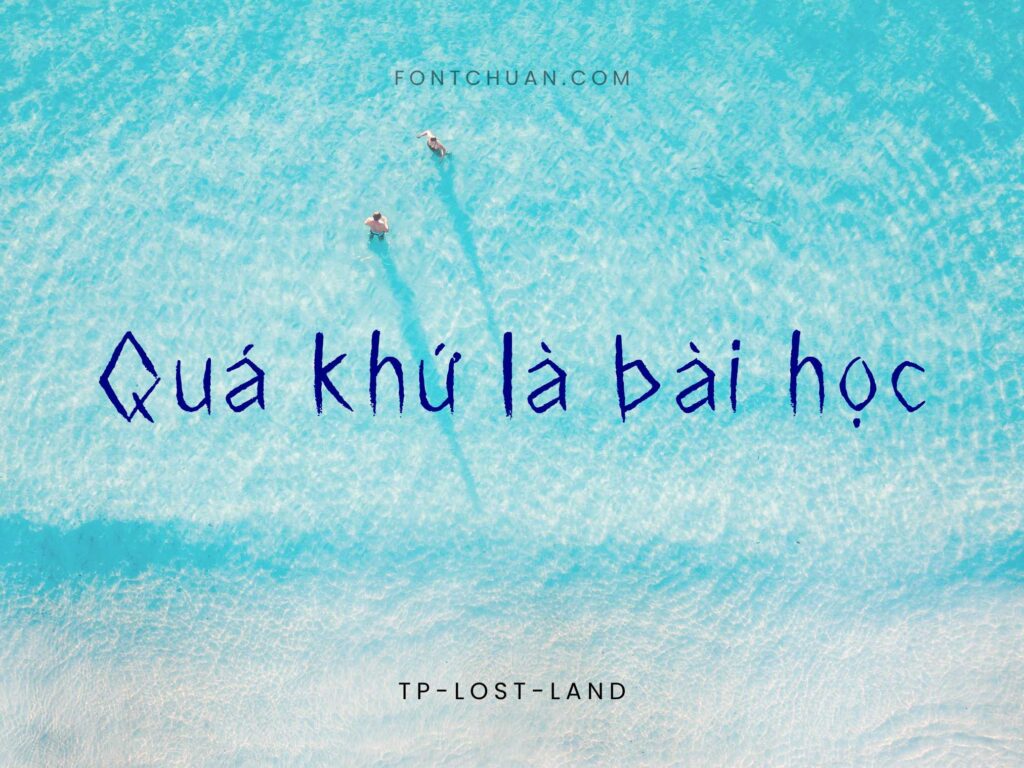
Font TP Lost Land Việt Hóa
Lost Land là một font chữ vẽ tay mang phong cách kinh dị, được thiết kế bởi Luiza Gasparyan và phát hành bởi Umbra95. Font này được tạo ra để sử dụng trong thiết kế bìa, logo, tiêu đề, thiết kế áo thun và tiêu đề tạp chí. Với các nét chữ độc đáo, hơi hướng kinh dị và mang phong cách hoài cổ, Lost Land còn có thể được sử dụng như một Font cổ trang, tạo nên vẻ bí ẩn và ấn tượng cho các dự án thiết kế mang yếu tố cổ điển hoặc huyền bí. Font đã được Việt hóa để hỗ trợ tiếng Việt bởi Tuỳn Pucca, giúp người dùng Việt Nam dễ dàng sử dụng trong các dự án thiết kế. Font này được sưu tầm và chia sẻ bởi thành viên của Font Chuẩn, đáp ứng nhu cầu sử dụng đa dạng trong cộng đồng thiết kế.
Đặc điểm thiết kế của Lost Land bao gồm các nét chữ không đồng đều, tạo cảm giác thủ công và nghệ thuật. Font này phù hợp cho các ứng dụng như thiết kế bìa sách, tiêu đề phim kinh dị, poster sự kiện và các dự án sáng tạo khác. Các ngành nghề phù hợp bao gồm quảng cáo, nghệ thuật và thiết kế đồ họa.